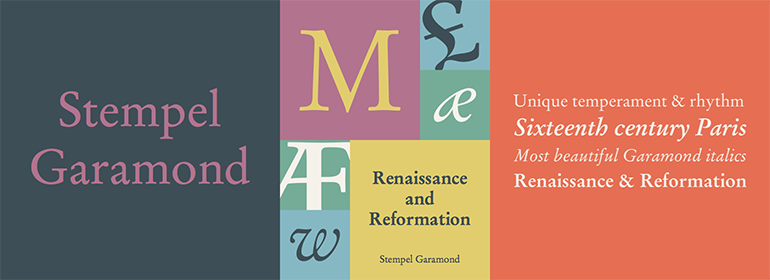
Stempel Garamond™
16世纪上半叶,Claude Garamond(约1480-1561年)为巴黎学者印刷商Robert Estienne刻字,其罗马体是根据Francesco Griffo在1495年为威尼斯印刷商Aldus Manutius切割的字体而设计的。Garamond在后来的版本中完善了其罗马体,随着他作为字冲雕刻师技能的提高,其中也加入了他自己的理念。在他1561年去世后,Garamond冲床被搬到了位于安特卫普的Christoph Plantin的印刷办公室,在这里被Plantin使用了数十年,至今仍保存于Plantin-Moretus博物馆中。Garamond的其他冲床都进入了Egenolff-Berner的法兰克福铸造厂,Egenolff-Berner于1592年发布了一个样本,成为后来的学者和设计师了解有关Garamond字体的一个重要的信息来源。1621年,即Garamond逝世六十年后,法国印刷商Jean Jannon(1580-1635)发行了一种字体样本,它的特征与Garamond设计类似,但是其字母的斜度和轴线更加不对称且不规则。Jannon的字体销声匿迹了大约200年,但1825年在法国国家印刷局被重新发现,当时它们被错误地认为是Claude Garamond。直到1927年Beatrice Warde的研究才揭示了它们的真正起源。20世纪早期,Jannon的字体被用来印刷一本法国的印刷史,这使人们重新注意到法国排印和Garamond字体。这激发了现代复兴的开始。一些基于Jannon字体的错误模型,而另一些则基于原始的Garamond字体。Garamond字体的斜体有时是基于Robert Granjon (1513-1589)切割的字体,Robert Granjon创作过Plantin,而且他的字体也在Egenolff-Berner的样本上。Linotype有多个Garamond版本的字体。虽然它们在设计和原型上各不相同,但它们均被视为法国文艺复兴时期风格的独特代表;它们的优雅和可读性都很易于识别。
Stempel Garamond™最早由D. Stempel AG于1925年首次发布,它是基于1592年的Egenolff-Berner样本,因此是真正的Garamond字体的复兴。它是对Garamond最著名的诠释之一,自1925年问世以来,它一直都是最常用的文本字体之一。Stempel Garamond具有自己独特的气质,其节奏和清晰度使它与其他的Garamonds区分开来。Stempel Garamond™有多种字重,包括小型大写字母,老式数字以及中欧字符。
Claude Garamond (ca. 1480-1561) cut types for the Parisian scholar-printer Robert Estienne in the first part of the sixteenth century, basing his romans on the types cut by Francesco Griffo for Venetian printer Aldus Manutius in 1495. Garamond refined his romans in later versions, adding his own concepts as he developed his skills as a punchcutter. After his death in 1561, the Garamond punches made their way to the printing office of Christoph Plantin in Antwerp, where they were used by Plantin for many decades, and still exist in the Plantin-Moretus museum. Other Garamond punches went to the Frankfurt foundry of Egenolff-Berner, who issued a specimen in 1592 that became an important source of information about the Garamond types for later scholars and designers. In 1621, sixty years after Garamond's death, the French printer Jean Jannon (1580-1635) issued a specimen of typefaces that had some characteristics similar to the Garamond designs, though his letters were more asymmetrical and irregular in slope and axis. Jannon's types disappeared from use for about two hundred years, but were re-discovered in the French national printing office in 1825, when they were wrongly attributed to Claude Garamond. Their true origin was not to be revealed until the 1927 research of Beatrice Warde. In the early 1900s, Jannon's types were used to print a history of printing in France, which brought new attention to French typography and the Garamond"" types. This sparked the beginning of modern revivals; some based on the mistaken model from Jannon's types, and others on the original Garamond types. Italics for Garamond fonts have sometimes been based on those cut by Robert Granjon (1513-1589), who worked for Plantin and whose types are also on the Egenolff-Berner specimen. Linotype has several versions of the Garamond typefaces. Though they vary in design and model of origin, they are all considered to be distinctive representations of French Renaissance style; easily recognizable by their elegance and readability.
First released by D. Stempel AG in 1925, Stempel Garamond™ was based on the Egenolff-Berner specimen of 1592 and was therefore a revival of the genuine Garamond types. It is one of the most famous Garamond interpretations, and since its introduction in 1925, it has been one of the most frequently used text fonts. Stempel Garamond has its own unique temperament, with a rhythm and sharpness that set it apart from other Garamonds. Stempel Garamond™ is available in several weights with small caps, Old style Figures, and Central European characters.